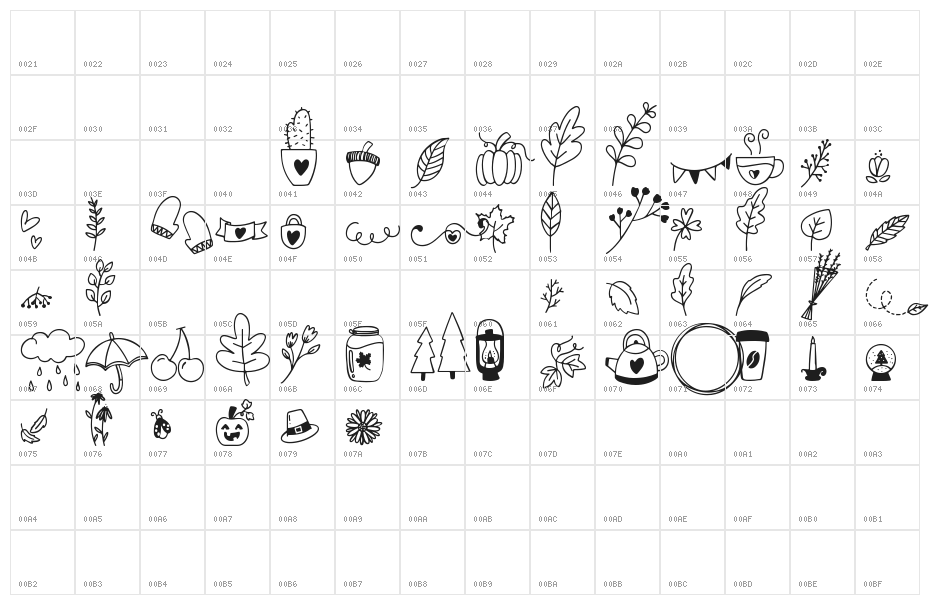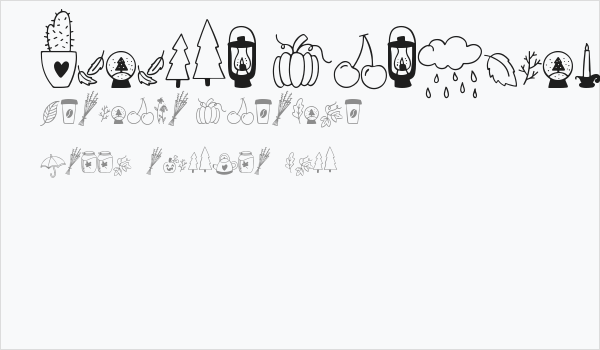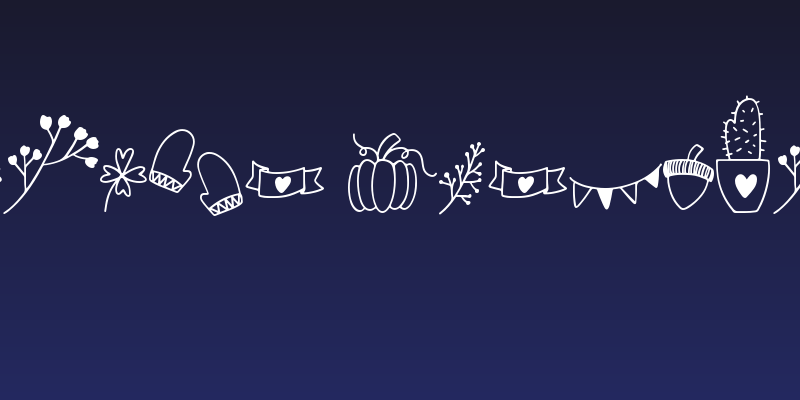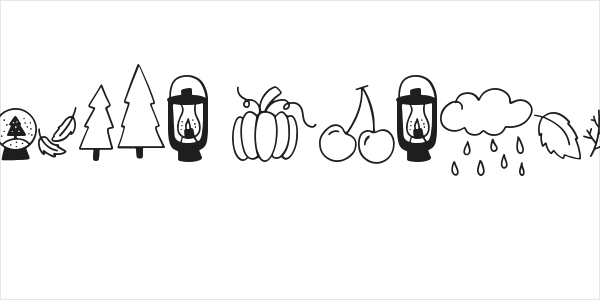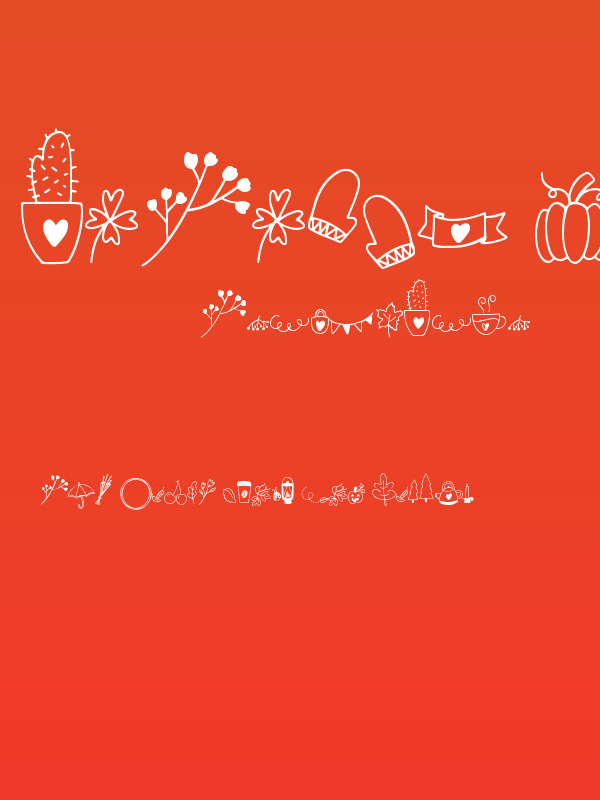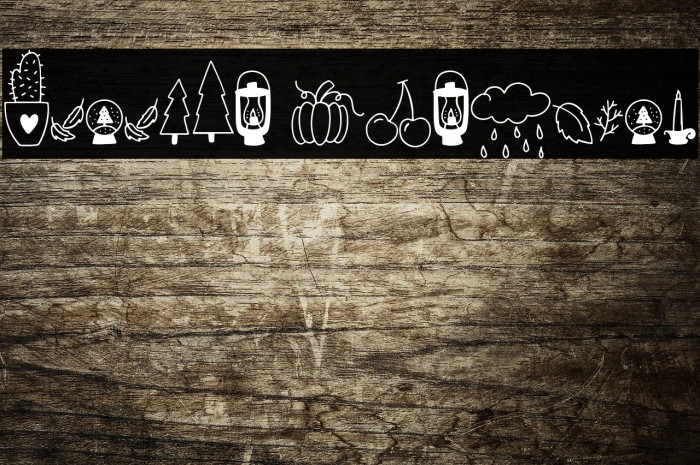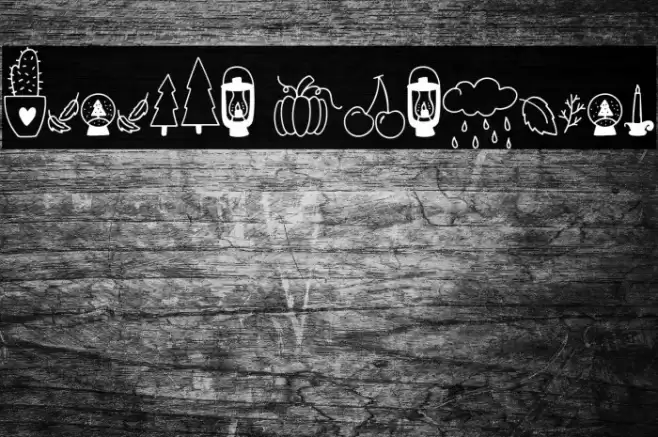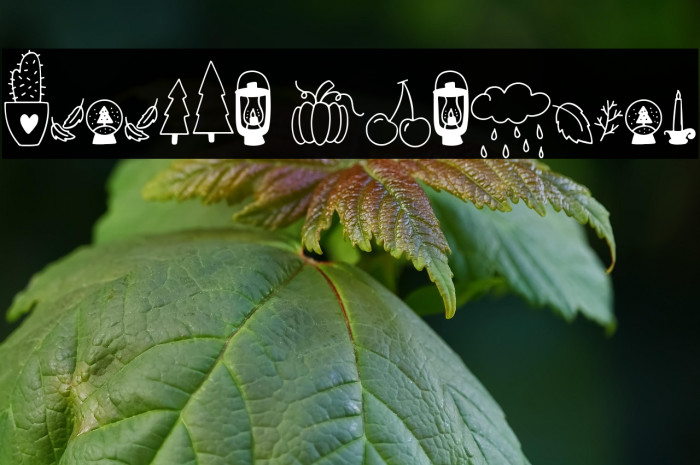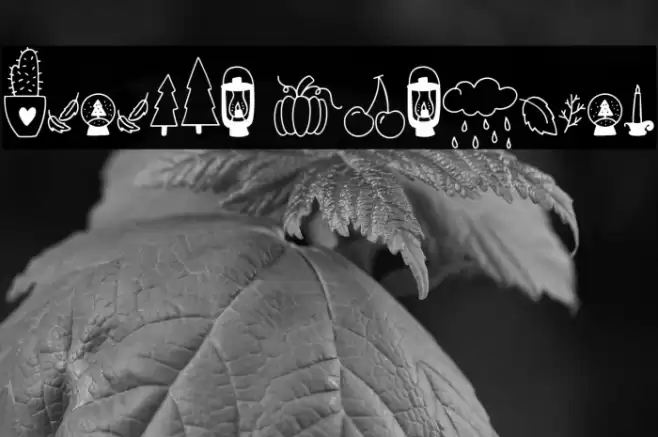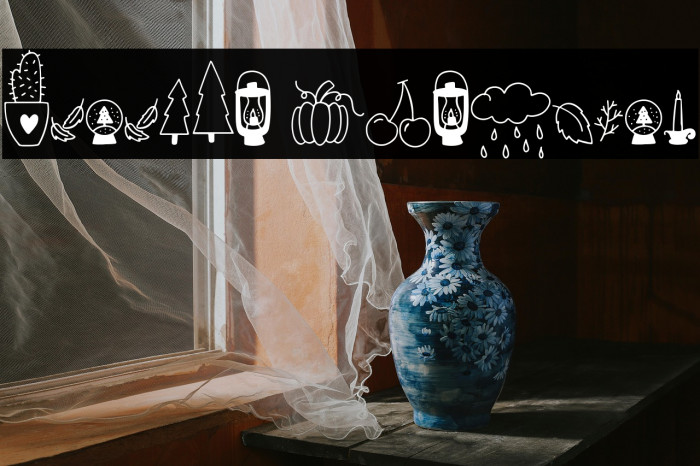
Autumn Dingbats Font
| Caso d'uso | Decorative elements, Seasonal designs |
| Progetti proposti | Ideal for seasonal greeting cards, fall-themed invitations, scrapbooking, and decorative elements in digital and print media. |